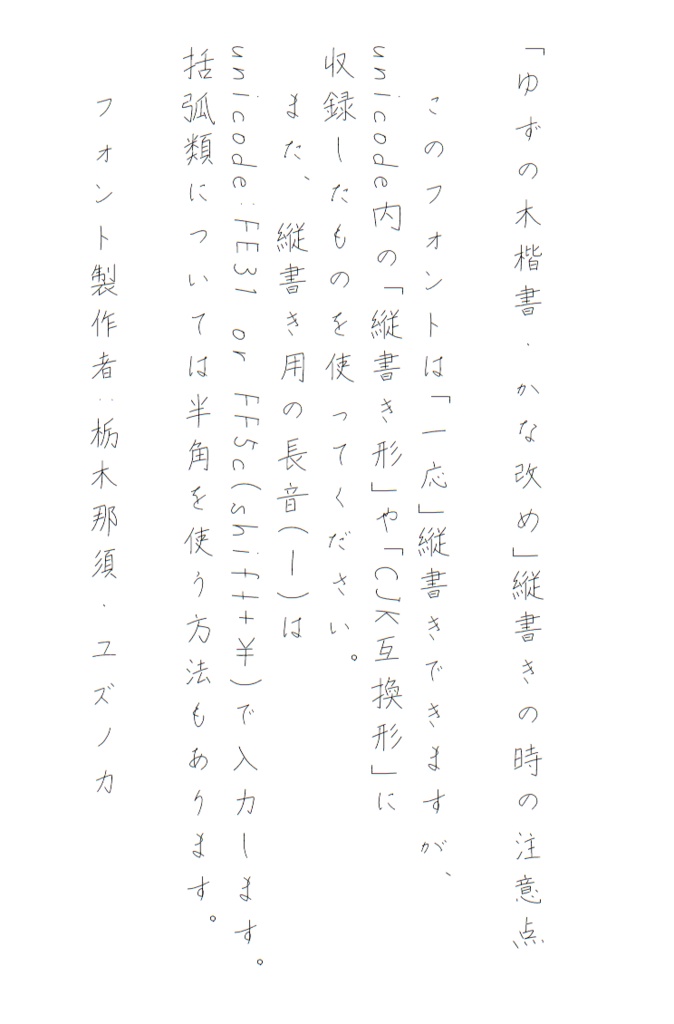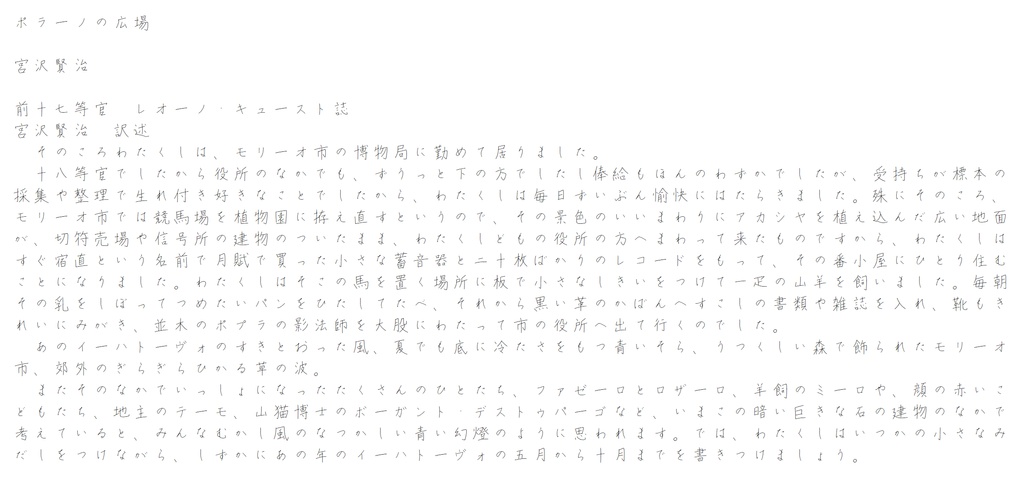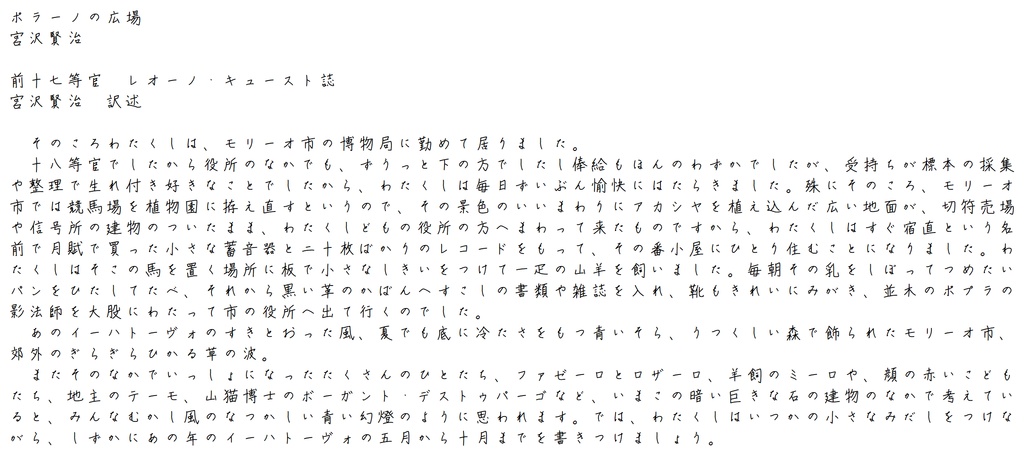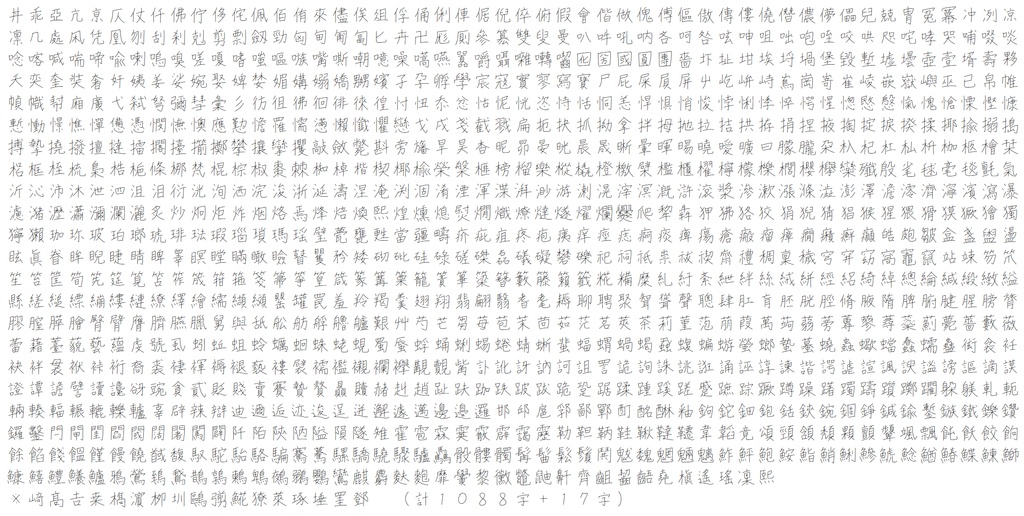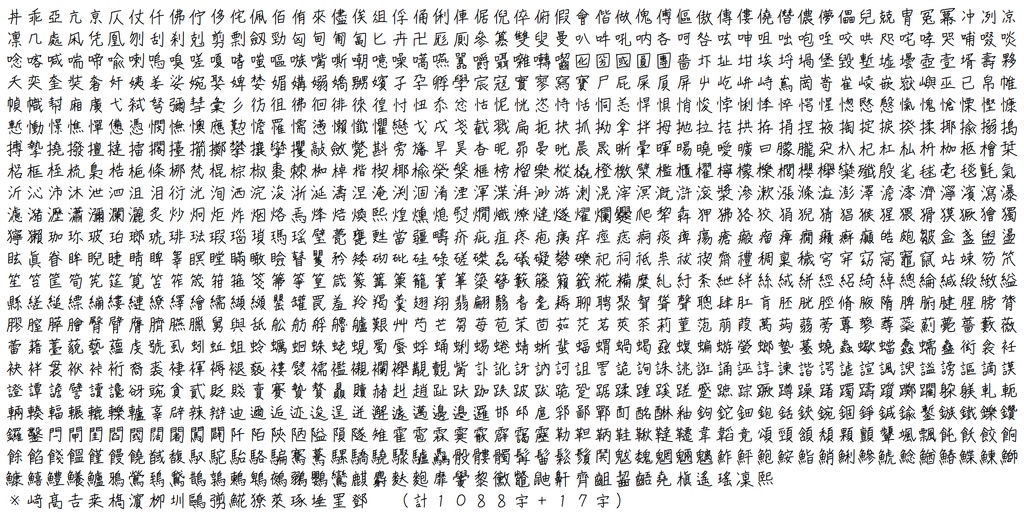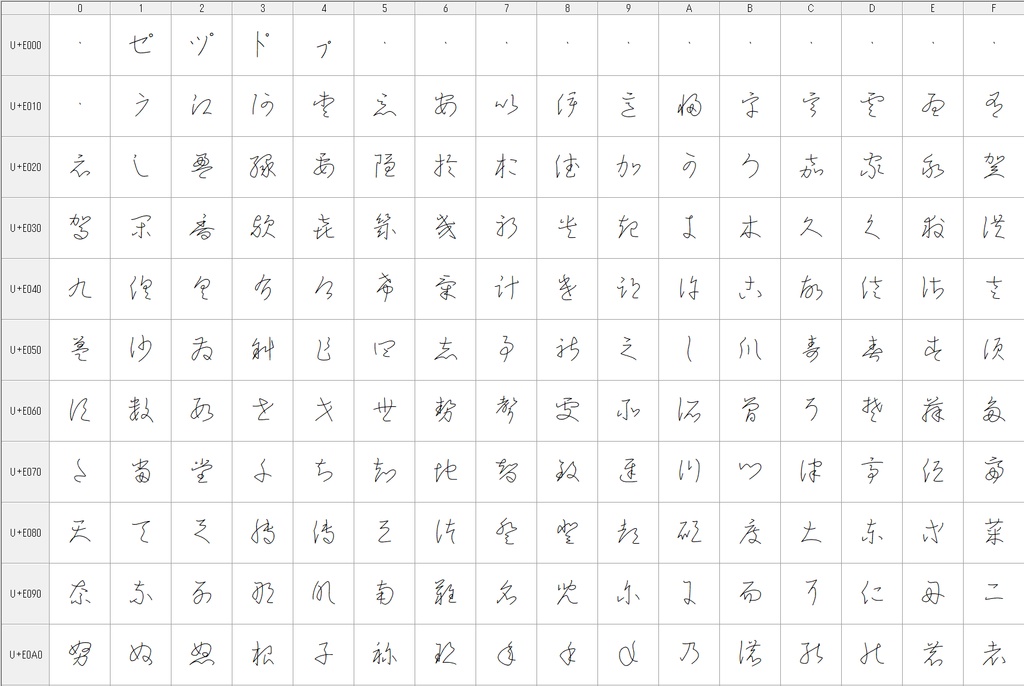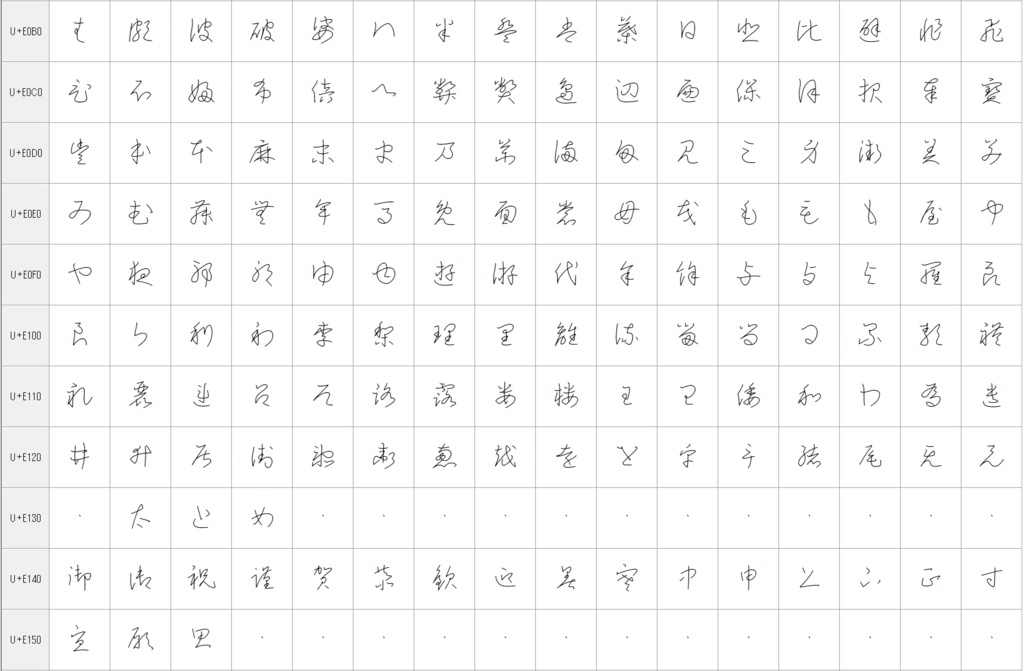
ゆずの木楷書・かな改めボールペン/サインペン(2024/10/06更新)
ゆずの木楷書・かな改め ボールペン/サインペン
このフォントは私自身の普段の手書き文字をフォント化した
「ゆずの木楷書」のひらがな・カタカナ部分を
より美しい仮名文字になるよう独自研究して
差し替えたバージョンで、漢字は「ゆずの木楷書」と共通です。
以前のバージョンを調整した太め版をあわせて公開しました。
収録文字:ひらがな、全角カタカナ、全角半角英数字、最低限の記号、
キリル文字、ギリシア文字、元号の合字、漢字4070字
(JIS第1水準漢字全部+JIS第2水準漢字一部+おまけ17字)
ひと通りの変体仮名と一部草書の漢字(私用領域に収録)
おまけで私用領域に一通りの変体仮名と一部草書を追加しました。
「御祝」「寸志」「迎春」「お見舞い申し上げます」などが書けます。